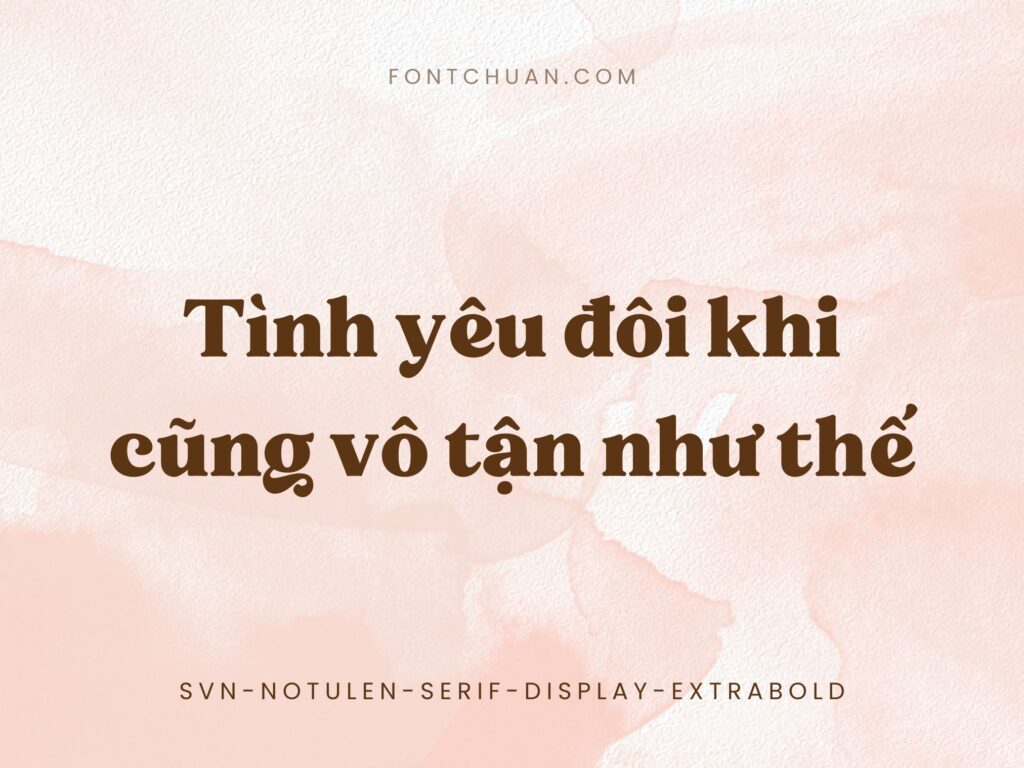
Font SVN Notulen Serif Display Extrabold Việt Hóa
Tác giả Font: Siwox Studios
Font SVN Notulen Serif Display ExtraBold là phiên bản Việt hóa của kiểu chữ Notulen Serif Display ExtraBold, được thực hiện bởi STYLEno.1 Fonts. Notulen là một kiểu chữ serif hiển thị với phong cách Extra Bold, được thiết kế bởi Siwox Studios. Font này lấy cảm hứng từ kiểu chữ cổ điển nhưng được kết hợp với nét hiện đại, tạo nên sự cân đối và thu hút. Các chân chữ ngắn với góc được bo tròn nhẹ giúp font dễ đọc ngay cả ở kích thước nhỏ. Notulen bao gồm đầy đủ các ký tự chữ hoa, chữ thường, chữ số và dấu câu, hỗ trợ đa ngôn ngữ. Font này phù hợp cho nhiều mục đích sử dụng khác nhau như thiết kế logo, tiêu đề, áp phích, bao bì sản phẩm, áo thun, thiệp mời và biển hiệu.
SVN Notulen Serif Display ExtraBold lý tưởng cho các dự án thiết kế yêu cầu sự mạnh mẽ và hiện đại, như thiết kế logo, tiêu đề, bao bì sản phẩm và các ấn phẩm truyền thông. Các ngành nghề như quảng cáo, bất động sản và giáo dục có thể tận dụng font này để tạo điểm nhấn trong thiết kế. Ngoài ra, font cũng thích hợp cho các sự kiện như Tết, Giáng sinh, Valentine và các lễ hội khác.